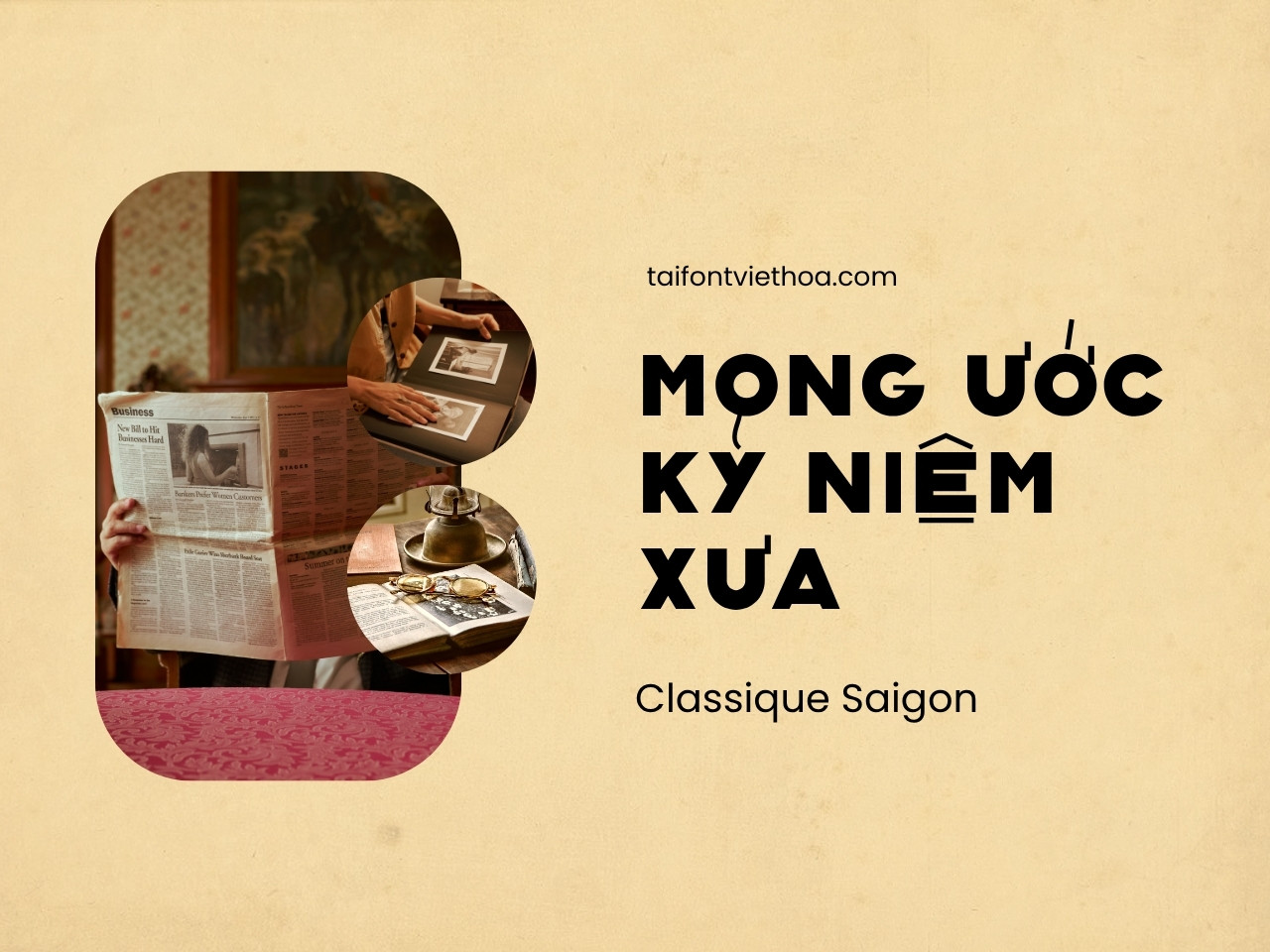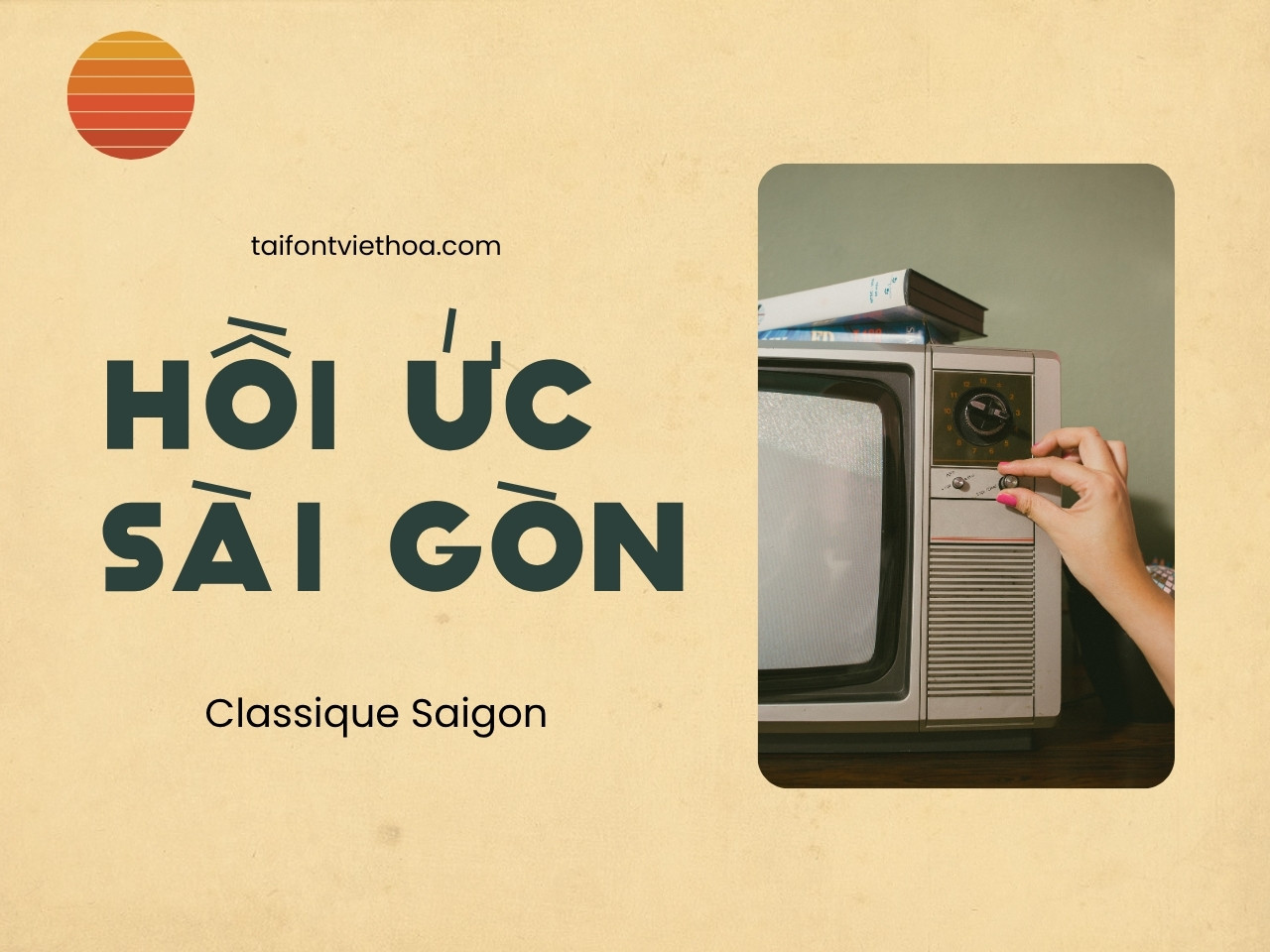
Font việt hóa Classique Saigon Typeface
Tác giả Font: Mạnh Nguyễn
Giới thiệu font Classique Saigon Typeface – Hơi thở hoài cổ của Sài Gòn thập niên 60s
Classique Saigon Typeface là một font chữ lấy cảm hứng từ các bảng hiệu và biển quảng cáo của Sài Gòn những năm 1960–1970, gắn liền với ký ức đô thị và tinh thần lãng mạn hoài cổ. Font được sáng tạo bởi nhà thiết kế người Việt – Mạnh Nguyễn – như một nỗ lực gìn giữ ký ức thị giác đặc trưng của miền Nam Việt Nam trong quá khứ. Phiên bản Việt hóa do chính tác giả thực hiện, đảm bảo hỗ trợ đầy đủ tiếng Việt và bộ ký tự mở rộng cho các ngôn ngữ khác. Font đã được taifontviethoa.com chọn lọc, sưu tầm và giới thiệu đến cộng đồng thiết kế Việt như một biểu tượng đồ họa của văn hóa đô thị xưa, phù hợp cho những dự án mang hơi thở vintage hoặc tôn vinh bản sắc truyền thống.
Giới thiệu font Classique Saigon Typeface – Hơi thở hoài cổ của Sài Gòn thập niên 60s
Đặc trưng hình khối cổ điển và ứng dụng của Classique Saigon
Font Classique Saigon có thiết kế sans-serif với các đường nét vuông vức, cứng cáp nhưng đồng thời vẫn giữ sự mềm mại nhờ cách xử lý đầu chữ uốn nhẹ. Font gợi nhớ đến bảng hiệu tiệm may, rạp chiếu bóng và hiệu sách xưa. Cấu trúc hình học ổn định giúp font phù hợp cho việc trình bày tiêu đề, logo thương hiệu, biển hiệu cửa hàng hoặc các ấn phẩm mang yếu tố hoài cổ. Đây là lựa chọn lý tưởng cho thiết kế poster lễ hội truyền thống, bao bì sản phẩm văn hóa, thiệp mời, bìa sách lịch sử – đ